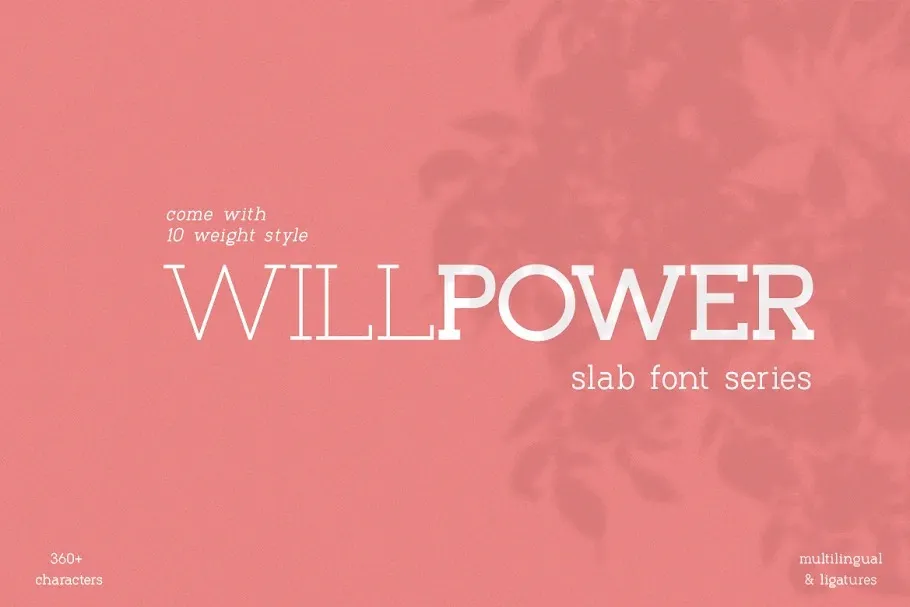
A font ‘Willpower’ é uma família de tipo com linhas de serif robustas e estilizadas para criar textos profissionais e envolventes. Esta font, criada por designers na plataforma 99designs, é perfeita para expressar uma mensagem clara em qualquer aplicação visual que você possa imaginar. Com um forte contraste entre o estilo robusto da serif e a sensibilidade humanista, ‘Willpower’ se destaca entre outras fontes de tipo. A família do Willpower conta com várias opções de peso: regular (5) e itálico (5), além de uma ampla gama de suporte para idiomas. Este conjunto de recursos linguísticos inclui 350+ caracteres, o que lhe dá a liberdade de escrever em quase qualquer língua do mundo. Com seu forte contraste entre linhas direitas e curvas romanas harmoniosamente combinadas, ‘Willpower’ foi projetada para escrita clara e facilmente legível. Perfeita tanto para criações branding e embalagens de produtos quanto para convites, citações, camisetas, etiquetas, headline, posters e logotipos. Além disso, sua estética robusta e moderna encaixa-se em uma variedade de aplicações gráficas, tornando-a perfeitamente adequada para projetar qualquer tipo de material visual que você possa estar criando.